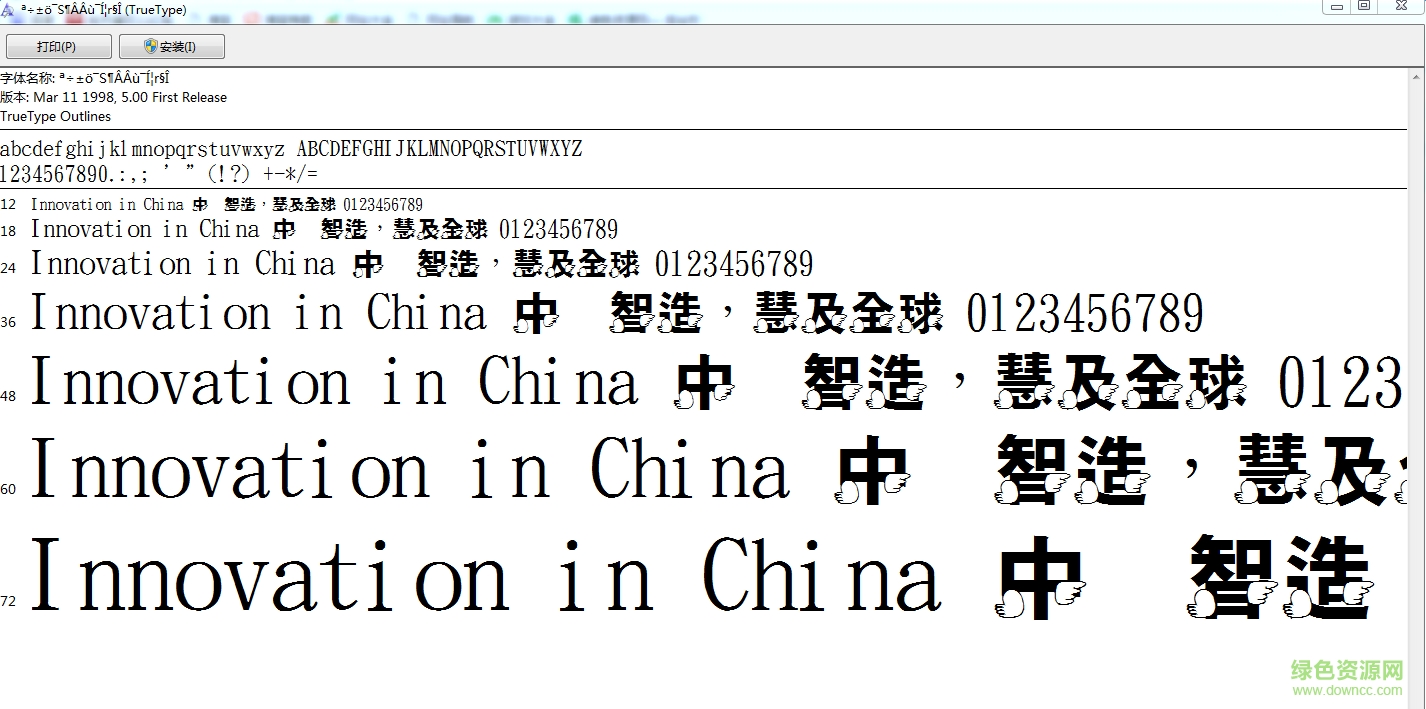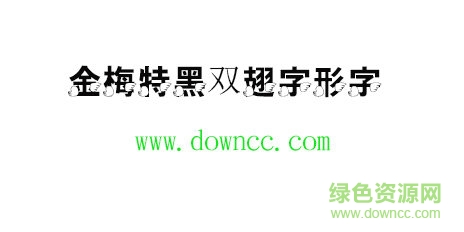
金梅特黑雙翅字形字體是一款金梅類(lèi)黑色字體軟件,黑色的字體給人非常舒服的感覺(jué),適合比較正規(guī)的場(chǎng)合,讓你的字體排版更加美觀大方,也比較的實(shí)用,還有更多好看的字體盡情期待,歡迎到綠色資源網(wǎng)下載體驗(yàn)!
金梅特黑雙翅字形是一款金梅類(lèi)黑色正規(guī)字體,字體效果比較黑,喜歡黑體字的朋友可以下載使用看看效果如何。